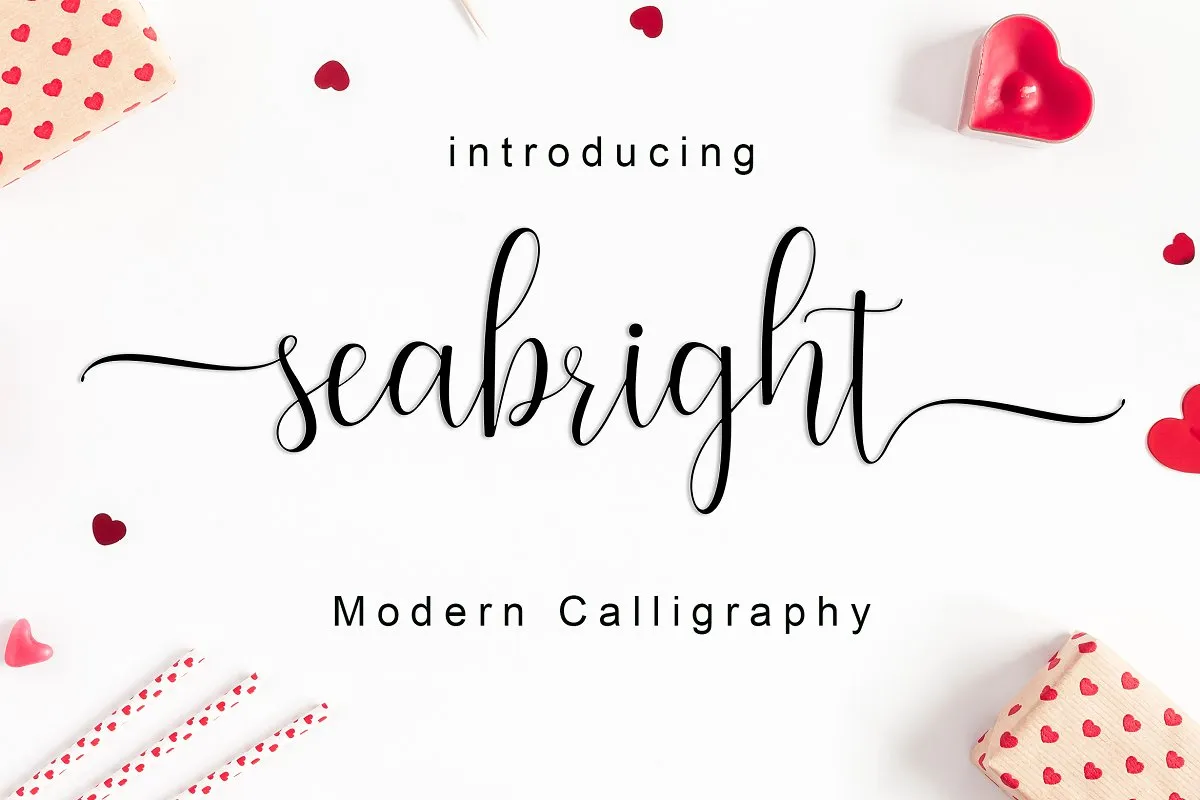
Seabright Script Font – Download Grátis
Aqui está uma descrição em português para a página de download da fonte ‘Seabright Script Font’, baseada na descrição original fornecida: Introduzimos hoje um novo estilo de fontes chamada Seabright, inspirado no caligrafismo. Criada manualmente pelo autor, esta fonte original é perfeitamente adequada para uso em qualquer projeto e qualquer situação. Seabright Script é uma opção ideal para artistas gráficos, designers ou ilustradores que buscam um estilo elegante e sofisticado na sua próxima criação. Com 250+ caracteres diferentes, incluindo alternativas personalizadas como Swash, Sets, Alternates e Alternatives Contextuais, Seabright oferece uma grande variedade de opções para adicionar ao seu trabalho. As alternativas em Open Type permitem a utilização fácil e intuitiva em ferramentas avançadas de design. Programas como Adobe Illustrator, Adobe InDesign, Adobe Photoshop, Corel Draw X ou até mesmo o Microsoft Word têm suporte para as funcionalidades abertas do tipo que permitem acessar facilmente todas essas alternativas. O PUA Unicode especializado (ou Punto a Universal) significa que você pode acessar e manipular todos os seus alterados caracteres com facilidade, sem qualquer problema de compatibilidade. Esta característica única permite que o artesão ou designer aproveite ao máximo as potencialidades deste design único para criar obras de arte digitais incríveis. Seabright é uma fonte versátil, elegante e poderosa, ideal tanto para projetos profissionais quanto para trabalhos pessoais. Com esta fonte na sua biblioteca, você ganha um recurso essencial que pode transformar o seu design em algo realmente especial.